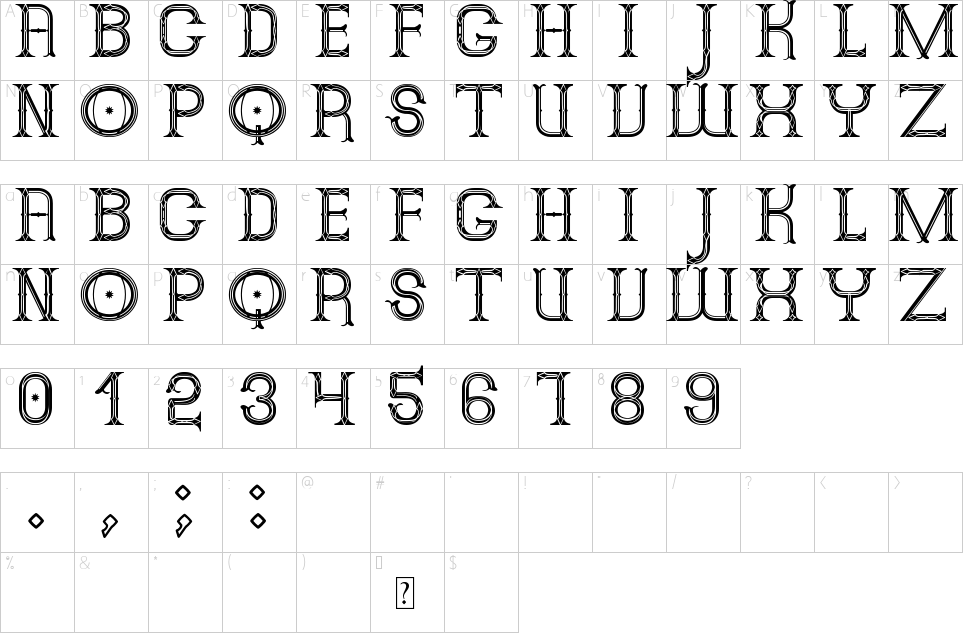
A fonte ‘Alphin Meritous Font’ é uma escolha perfeita para designers e profissionais de design gráfico que buscam uma fonte com um toque único e elegante. Desenvolvida pelo Southype, esta fonte vem em versões para Windows e Mac, e tem sido baixada mais de 11.163 vezes. A sua elegância e profissionalismo são características distintas desta fonte, tornando-a uma opção popular para criações de alta qualidade. Com suas linhas suaves e sutis, a ‘Alphin Meritous Font’ é uma escolha ideal para personalizar materiais de marketing, designs de página web e até mesmo para adicionar um toque sofisticado a qualquer projeto. Com sua versão gratuita, os designers podem experimentar a qualidade e a facilidade de uso desta fonte, sem preocupações de custos adicionais.